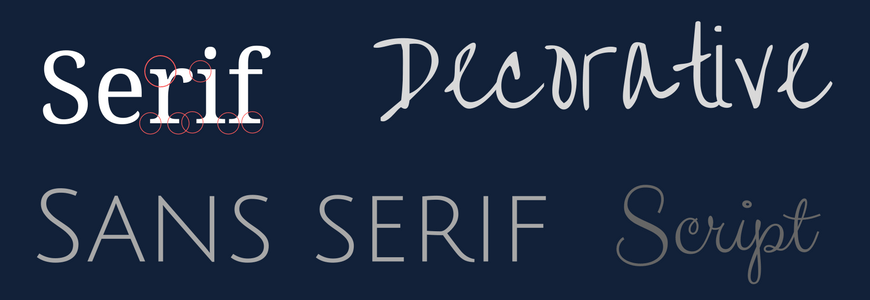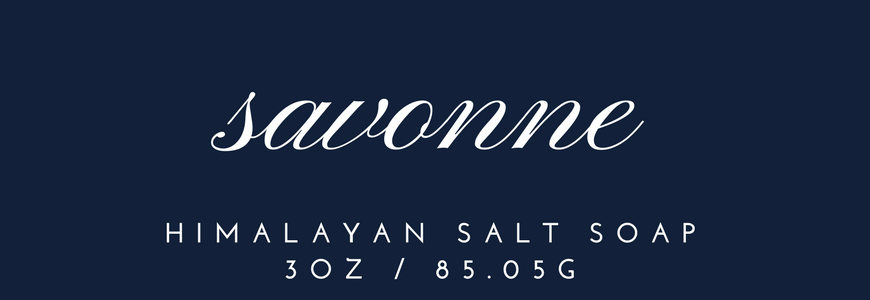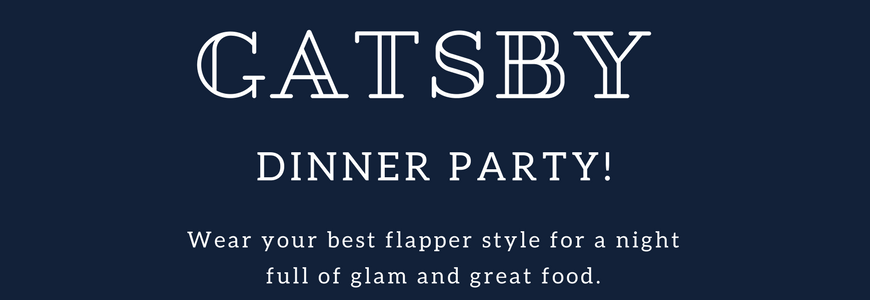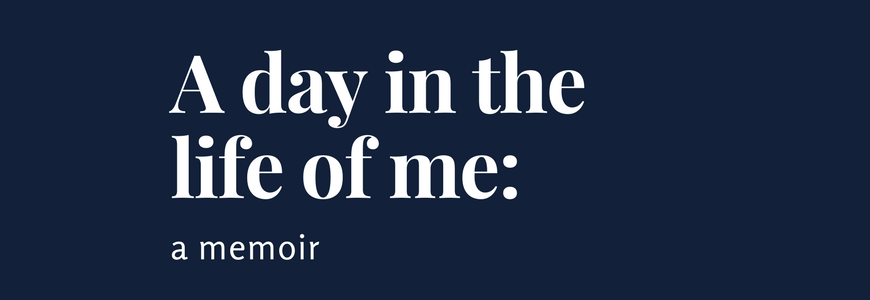
5 советов по сочетанию шрифтов
Словосочетание «комбинирование шрифтов» для кого-то звучит невероятно привлекательно, а кого-то повергает в уныние. Далеко не все дизайнеры любят возиться со шрифтами. Но почему так важно правильно сочетать шрифты? Есть ли способ сделать это быстро и забыть? Теоретически можно, но это не совсем в ваших интересах.
Выбор хорошо сочетающихся шрифтов поможет вашей странице быть более функциональной и эстетически привлекательнее. Также это ваш графический интерфейс будет выглядеть профессионально-выполненным, а текст будет хорошо читаться.
Два шрифта необязательно будут хорошо смотреться вместе, даже если каждый из них в отдельности вам нравится. Какими бы замечательными они ни были, шрифты вполне могут не сочетаться, а это плохо скажется на вашем дизайне.
В этой статье мы рассмотрим лучшие сочетания шрифтов, которые хорошо работают вместе в дизайне сайта, графики и полиграфии.
Важность правильного сочетания шрифтов
Почему так важно, чтобы шрифты хорошо сочетались? Все просто. Неправильно подобранные гарнитуры усложняют пользователю чтение контента. Когда вам приходится прилагать усилия, для того, чтобы прочесть текст, велика вероятность того, что вы просто передумаете его читать.
Так же как и с цветовой схемой, чтобы обеспечить вовлеченность пользователя, правильные сочетания необходимы. Важно подобрать такой шрифт, чтобы ваш заголовок явно выделялся на фоне остального текста, и пользователи точно понимали что это он. В случае с заголовком ограничений не так много, как с основным текстом, и здесь вы можете выйти за рамки.
А вот основной текст должно быть легко читать, так как именно его будет больше всего на вашей странице. Ну и конечно вся типографика — и основной текст,  и заголовки и подзаголовки — должны правильно работать вместе.
Понимание различия шрифтов
Прежде чем мы начнем разбирать сочетаемость шрифтов, давайте быстро пройдемся по типа гарнитур.
Шрифты с засечками
Шрифты с засечками отличаются тем, что буквы начинаются и заканчиваются штрихом.
Шрифты без засечек
У этого типа шрифтов напротив нет штрихов.
Рукописные шрифты
Эти шрифты имитируют письмо от руки. Часто буквы соприкасаются, переходя друг в друга.
Декоративные шрифты
Это самая разнообразная группа шрифтов. Декоративные шрифты могут быть очень разными, и используются в основном в заголовках или надписях, и почти никогда для текстов большого объема.
Как правильно подобрать сочетание
Теперь, когда мы разобрались с тем, какие бывают шрифты, давайте посмотрим как они работают вместе.
Вот несколько подсказок, которые помогут вам правильно выбрать гарнитуры, которые будут соседствовать на странице.
1. Контраст вместо конкуренции
Шрифты должны контрастировать, а не конкурировать на странице. К примеру, два декоративных шрифта скорее всего будут конкурировать за внимание пользование.
Чтобы этого не происходило, выбирайте один декоративный или рукописный шрифт, а второй — с засечками.
Главное при подборе двух шрифтов, чтобы они не были слишком схожи. Гарнитуры должны различаться настолько, чтобы пользователь четко видел различия.
Чтобы добиться этого абсолютно точно, вы можете экспериментировать с жирным и наклонным вариантами шрифтов. Это также поможет создать то, что в дизайнерском мире называется иерархией контента.
Иерархия в типографике это когда когда заголовок очевидно больше подзаголовка, подзаголовок больше обычного текста.
2.  Найдите большое и классное семейство шрифтов
Когда вы найдете семейство шрифтов, которое вам действительно понравится, самая тяжелая часть по созданию типографической иерархии будет сделана за вас.
В идеале, такое «супер-семейство» должно включать шрифты с засечками и без, а также их варианты в жирном и наклонном виде.
Такой набор очень полезен, потому что вы можете быть уверены, что эти шрифты хорошо работают вместе, раз они являются частью одного семейства. Все что вам нужно — выбрать нужные вариации.
3.  Не используйте больше трех разных шрифтов
У каждого шрифта своя личность. Когда их много, разные шрифты плохо работают вместе, как много хозяек на одной кухне.
Ограничьтесь одним-двумя шрифтами, чтобы избежать ощущения перегруженности дизайна и хаоса в типографике на странице.
4. Работайте с кернингом
Кернинг — это интервалы между буквами. Не бойтесь экспериментировать с этим значением, и вы сможете добиться действительно хороших результатов.
Однако далеко не все шрифты хорошо выглядят с увеличенным межбуквенным расстоянием.
Например, для рукописных шрифтов увеличение кернинга чаще всего сделает шрифт менее плавным, буквы не будут перетекать одна в другую.
А вот в надписях, где все буквы заглавные, увеличение интервала между символами часто выглядит хорошо.
В этом примере слово “mozzarella” написано рукописным шрифтом со стандартным расстоянием между буквами, а подзаголовок “the superior cheese” выведено заглавными буквами, шрифтом без засечек и с увеличенным кернингом.
5.  Не используйте заезженные шрифты
Использовать в дизайне заезженные, набившие оскомину шрифты — большой дизайнерский грех. Это может отвлечь от самого дизайна, вызвать недоверие. Да и зачем использовать то, что уже всем надоело, когда так много свежих и качественных вариантов?
Некоторые из заезженных шрифтов: Comic Sans, Impact, Arial, Bradley Hand, and Papyrus.
Хорошие примеры сочетаний
Давайте посмотрим несколько неплохих примеров сочетания шрифтов. В этих примерах наглядно продемонстрированы примеры, о которых мы говорили выше.
Pinyon Script и Josefin Sans
Эти два шрифта хорошо смотрятся вместе благодаря плавности и текучести рукописного шрифта и простоты шрифта без засечек с увеличенным кернингом.
Рукописный шрифт привлекает внимание, а шрифт без засечек дополняет его, описывая более объемную, уточняющую информацию.
pinyon example
Playfair Display и Rosario
Солидный и крупный шрифт Playfair Display в заголовке и тонкий, лаконичным Rosario в подзаголовке создают отличную пару в этой ситуации.
Гарнитуры не отвлекают внимание друг от друга и хорошо работают вместе.
Pirou и Aleo
А вот пример, в котором использовано два шрифта, но один из них — в двух вариациях.
Игривый Pirou выделяет слово “Gatsby”. А простой Aleo отлично его дополняет.
Еще более интересным это сочетание выглядит из-за того, что заголовок и подзаголовок написаны заглавными буквами, а основной текст — обычным способом.
Здесь также четко подана иерархия. Читатель сразу понимает какой текст самый важный, какой второстепенный и какой описывает детали.